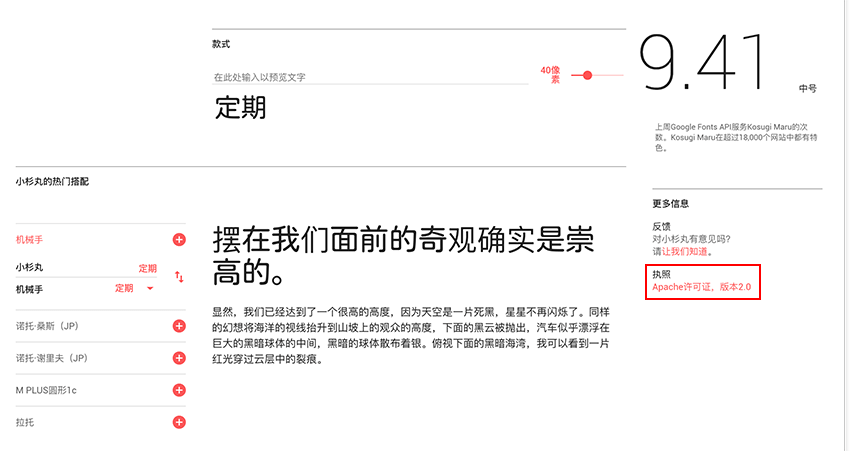
小杉圓體MotoyaLMaru 詳情頁
圓體
小杉圓體全名 Motoya Kosugi Maru,是一款免費開源的日本字體。最初是由MOTOYA公司為Android平臺所開發(fā)的圓體, 現(xiàn)在在Google font可下載,以 JIS 第1水準(zhǔn)和第2水準(zhǔn)進(jìn)行開發(fā),目前字?jǐn)?shù)共有 7,573 字,已經(jīng)于許多 Android 手機內(nèi)建使用,是以Apache 2.0 License進(jìn)行開源發(fā)佈,可自由改作,但須以同樣方式進(jìn)行開源發(fā)佈。